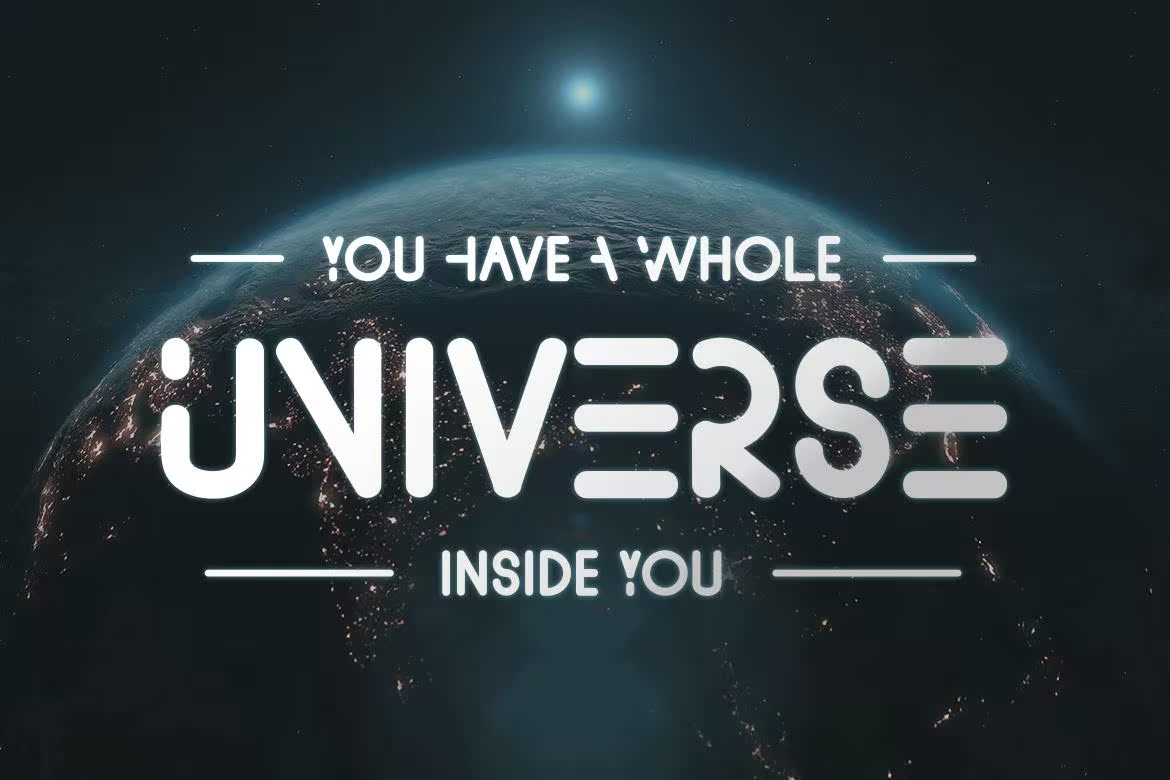
MadsenseisauturisticFontfordesignofminimalisticLogo和Rebrand。MadsenseisauturisticFontfordesignofminimalisticLogo和Rebrand.Madsenseihas DigitalWorldFeel。可用于创建文字标记的内容,书名、封面、fontgame、电子竞技、标语和现代技术内饰主题。